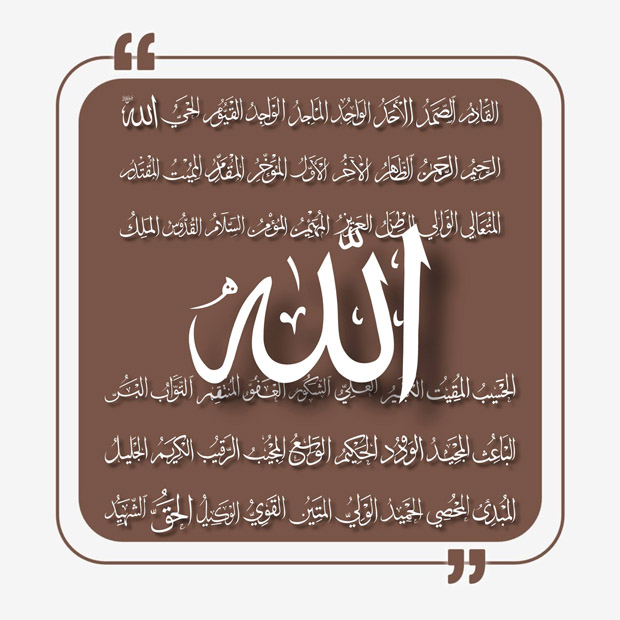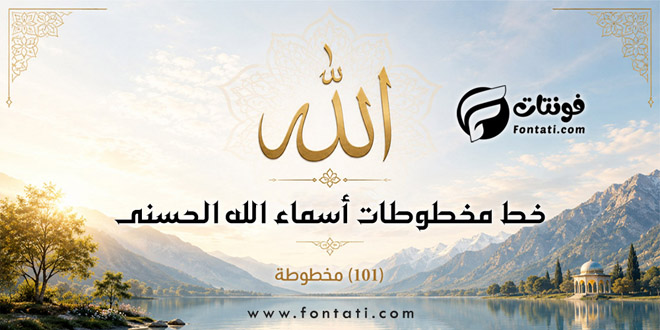
خط مخطوطات أسماء الله الحسنى .. خط أكثر من رائع يحتوي على مخطوطات أسماء الله الحسنى سبحانه وتعالى، يمكن الكتابة بالخط حسب الدليل المرفق وذلك بكتابة الأرقام الإنجليزية من (1) إلى رقم (101)، وهو متاح للتحميل المجاني الآن.